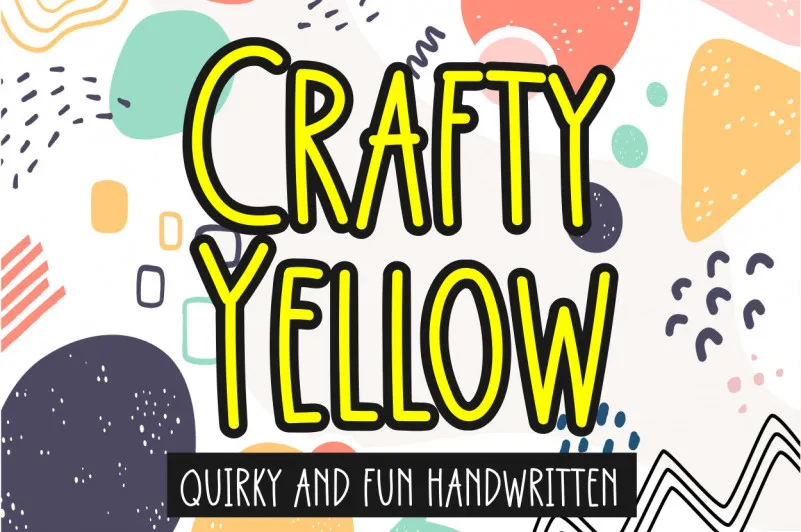
A fonte Crafty Yellow é uma opção perfeita para quem busca personalidade e simplicidade no design, criando um ar divertido e quixotesco que encaixa-se perfeitamente tanto nas produções infanto-juvenis quanto nos desenhos animados. Ela se destaca por sua leitura agradável, proporcionando uma pitada de humor e originalidade à qualquer projeto. Ideal para designers de games infantis, ilustradores criativos ou quem precisa de um toque encantado em seus projetos digitais, esta fonte oferece uma escolha única que certamente fará da sua criação algo especial. Com sua estética fluida e escrita a mão, Crafty Yellow é perfeita para dar vida às suas ideias, seja para animações de filmes infantis ou até mesmo para design gráfico mais elaborado. Ela não apenas adicionará um toque divertido à sua obra, mas também certamente deixará uma impressão duradoura no público final.